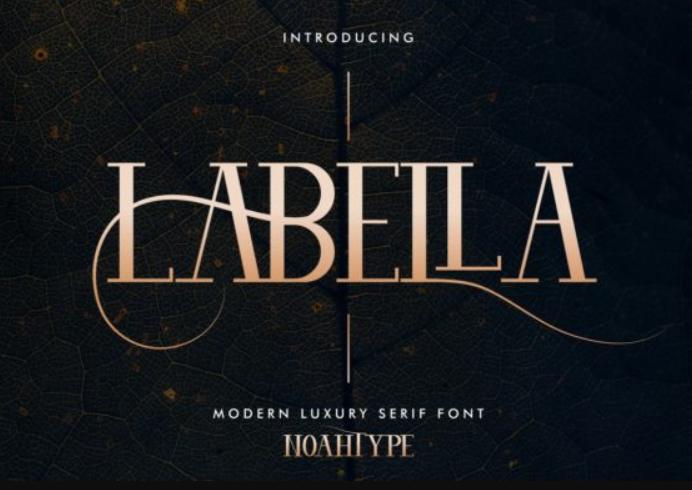
[Creativefabrica] Labella Font (NoahType)
Labella - классический шрифт с засечками в потрясающем стиле. Шрифт был вдохновлен винтажными классическими буквами. В нем есть уникальные персонажи, которые привнесут особый эффект в ваш дизайн. Он хорошо подходит для свадеб, брендинга, девушек, художников, макияжа, заголовков, логотипов, плакатов, названий, продуктов и т. д. Этот шрифт имеет кодировку PUA, что означает, что вы можете легко получить доступ ко всем глифам и росчеркам!